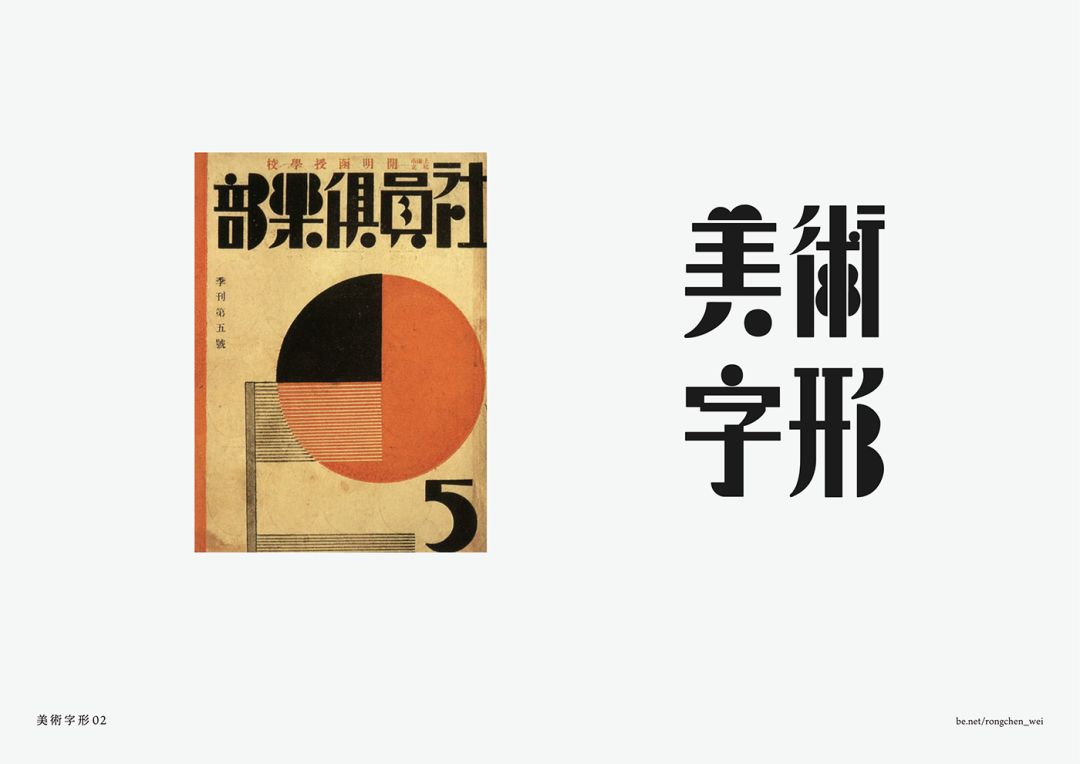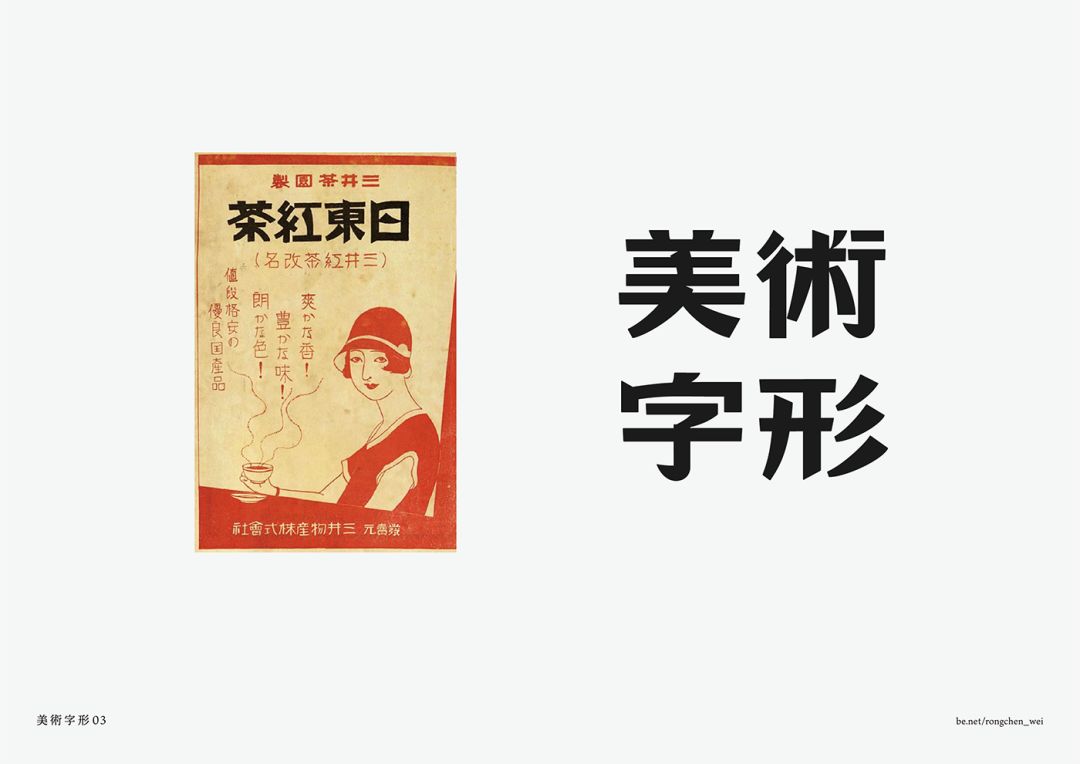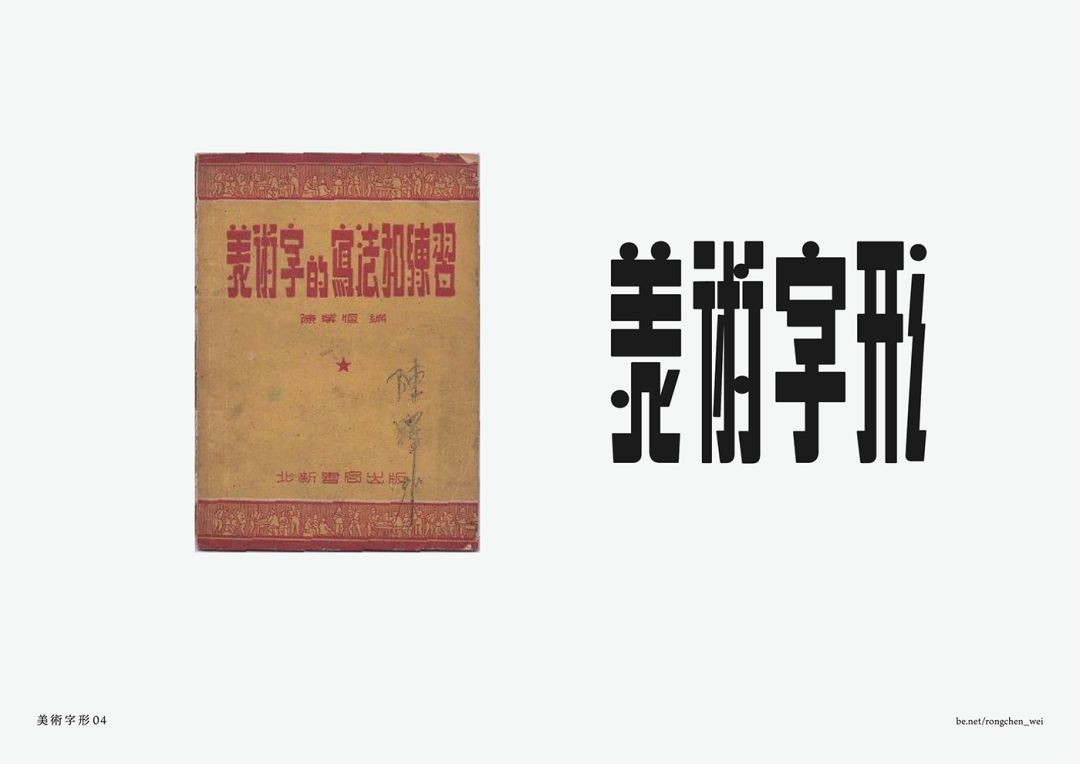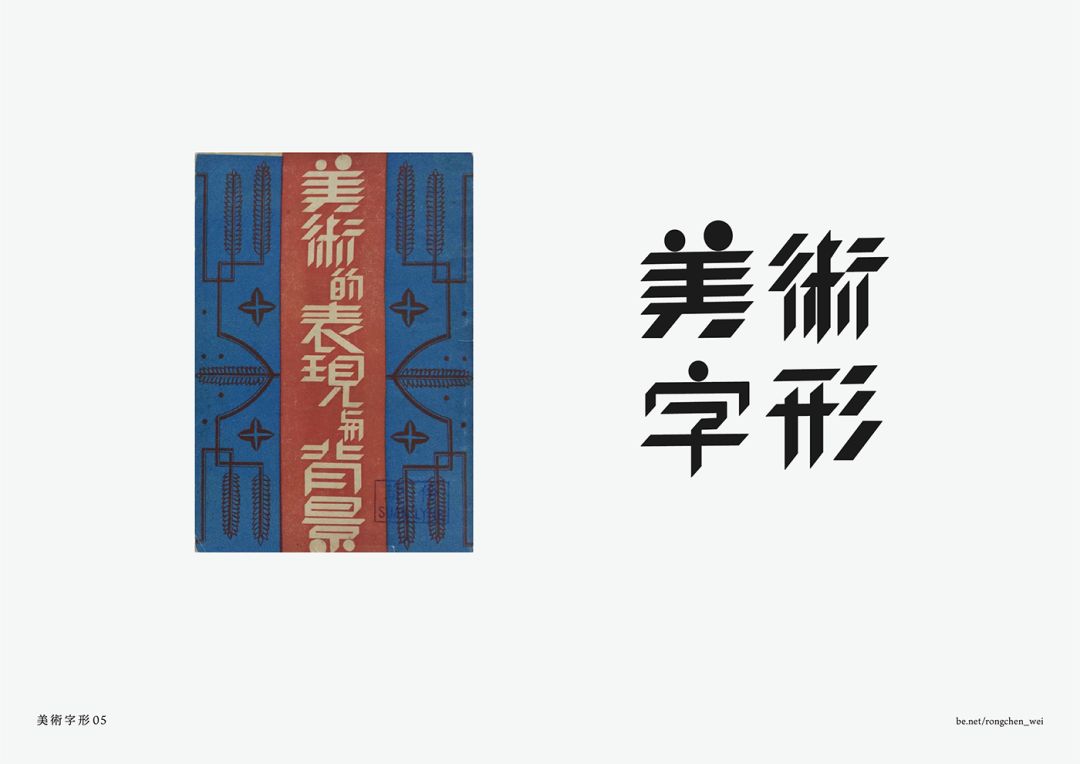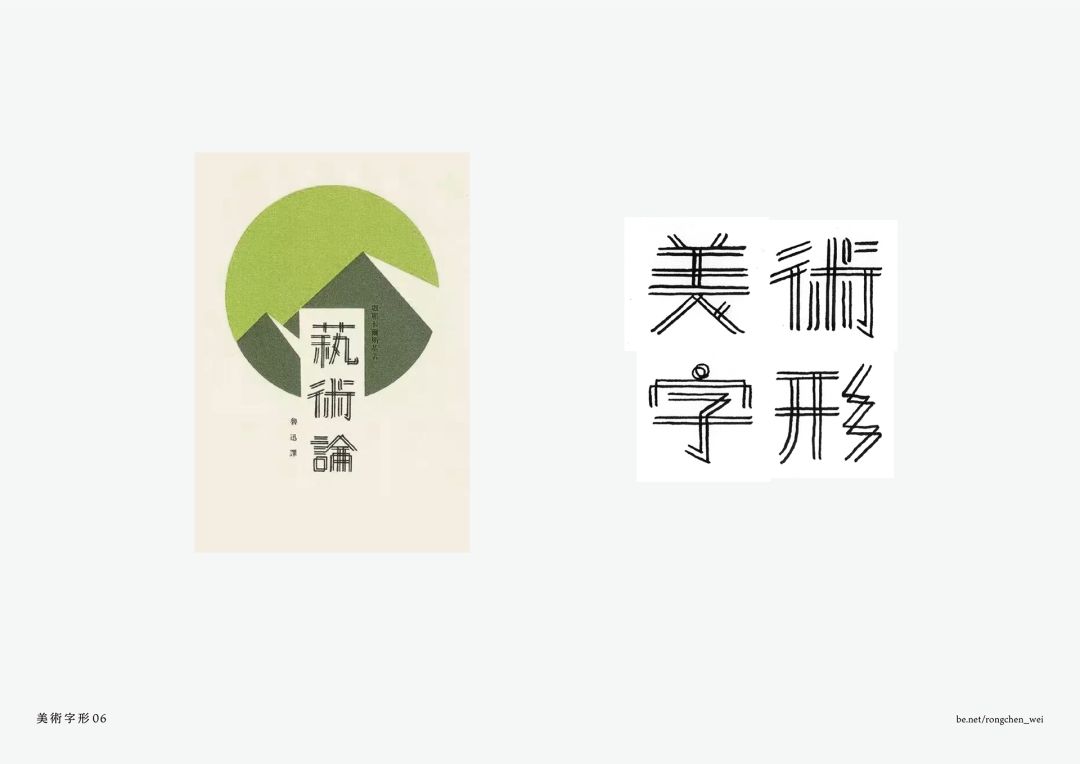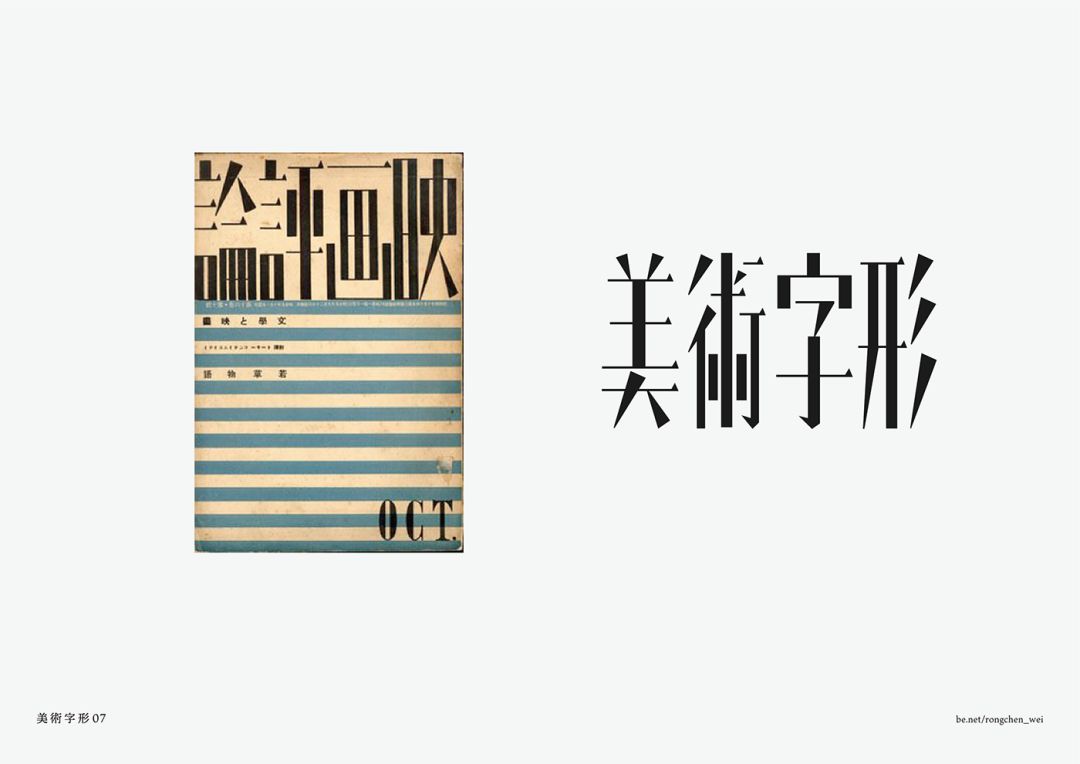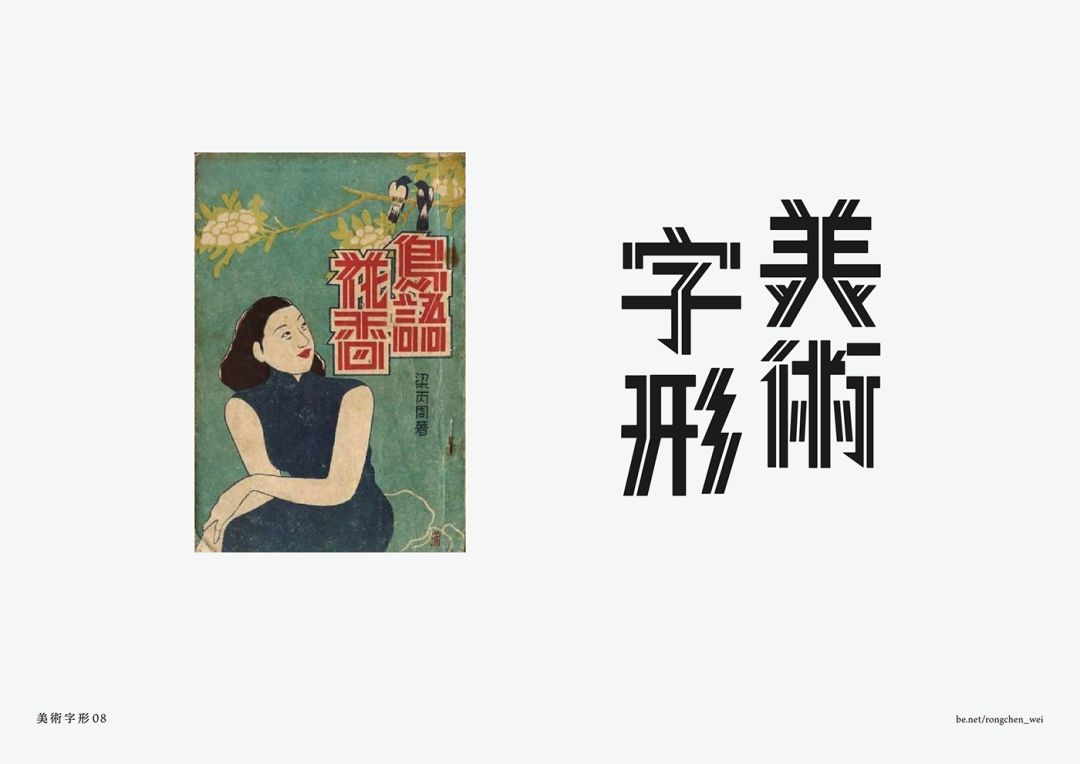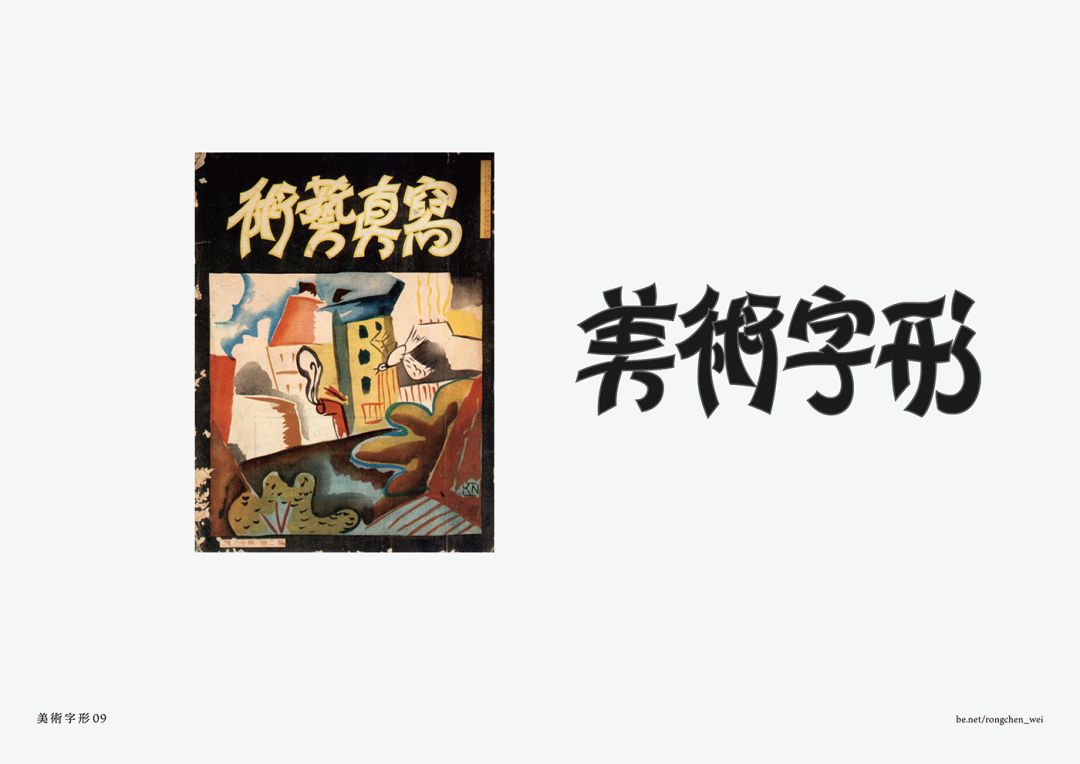
复古美术字再造!复古美术字分享
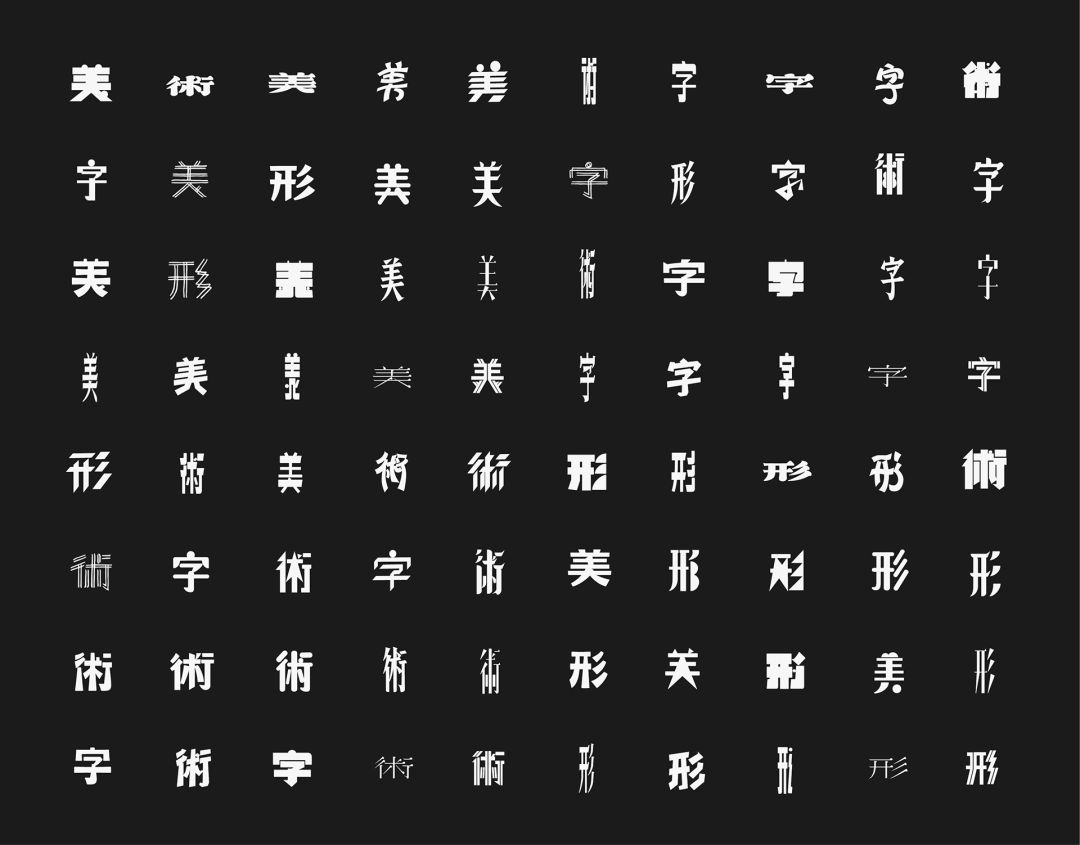
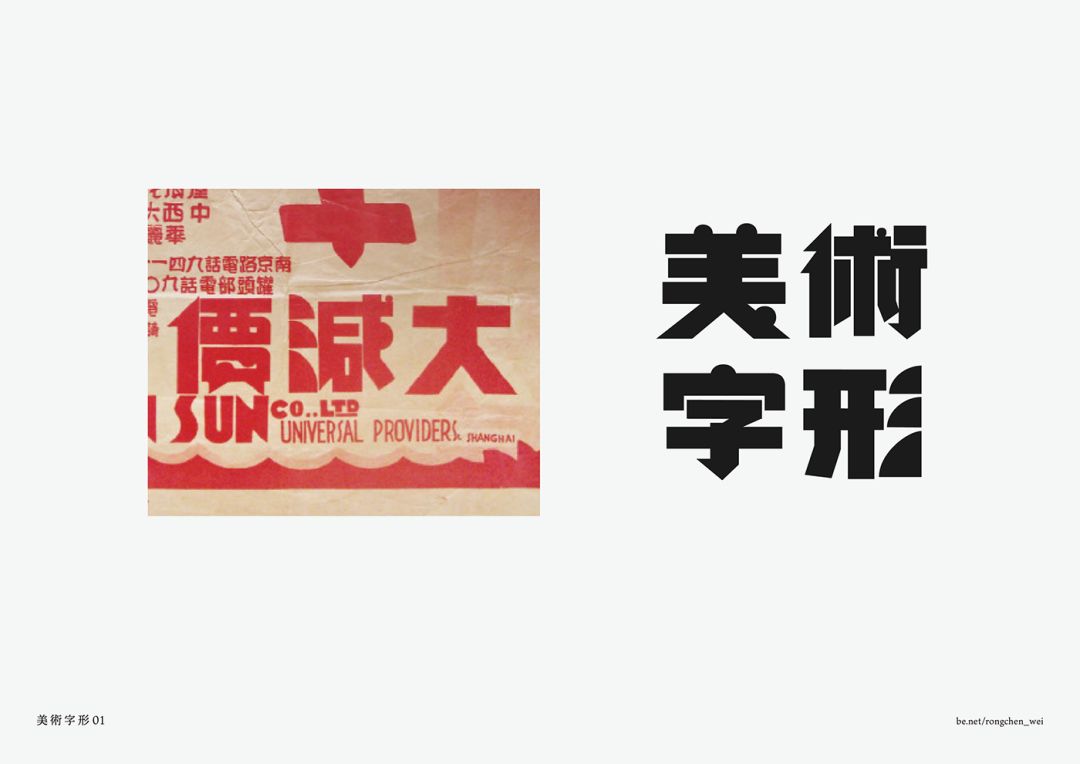
再造背景 Background
二十世纪初,可谓是中文美术字的黄金时代,魏荣辰认为所有创意的形式,可能都在这时期发生。在创作美玲体时(这位台湾设计师开发了一套复古文字—美玲體),魏荣辰陆陆续续从网路与其他设计师收集许多民初时期的文宣品,每看一遍都心生讚叹,因此萌生复刻的念头。
美术字是一种运用装饰手法美化文字的书写艺术,以一种独立的姿态兼并传统艺术,并带有商业文化的特质积极加入到中国汉字艺术文化范式的再造过程中。广告中的美术字可谓是近现代美术字案例的巨大宝库,不同的字体类型,不同的风格,不同的组合形式,反映出当时人们对于字体革新、商业环境影响与审美方式诉求的状况。